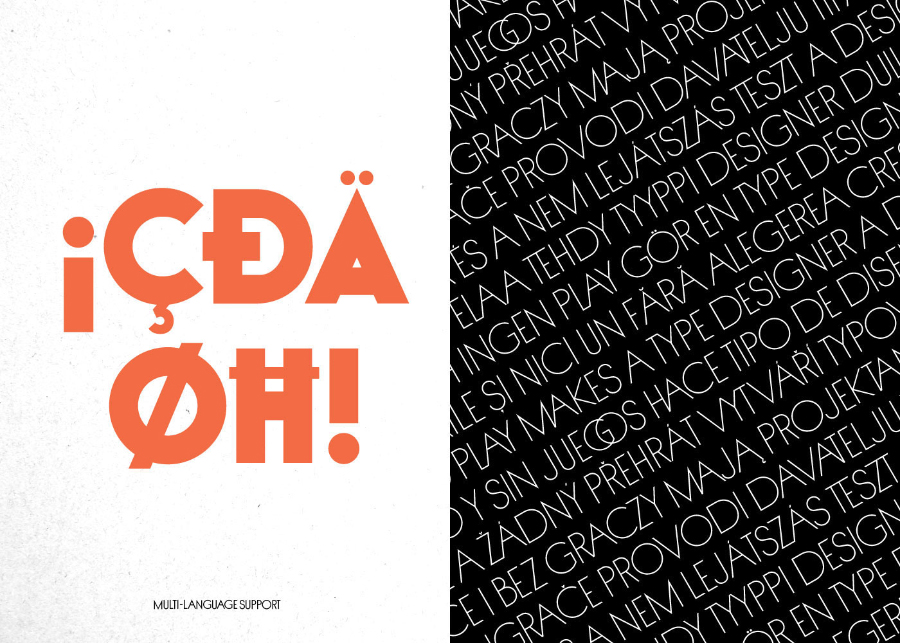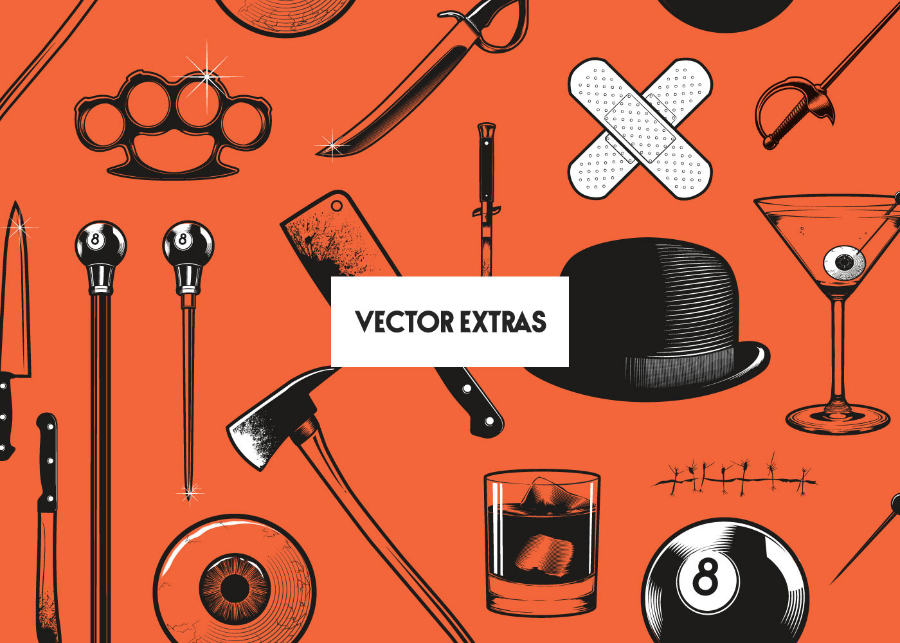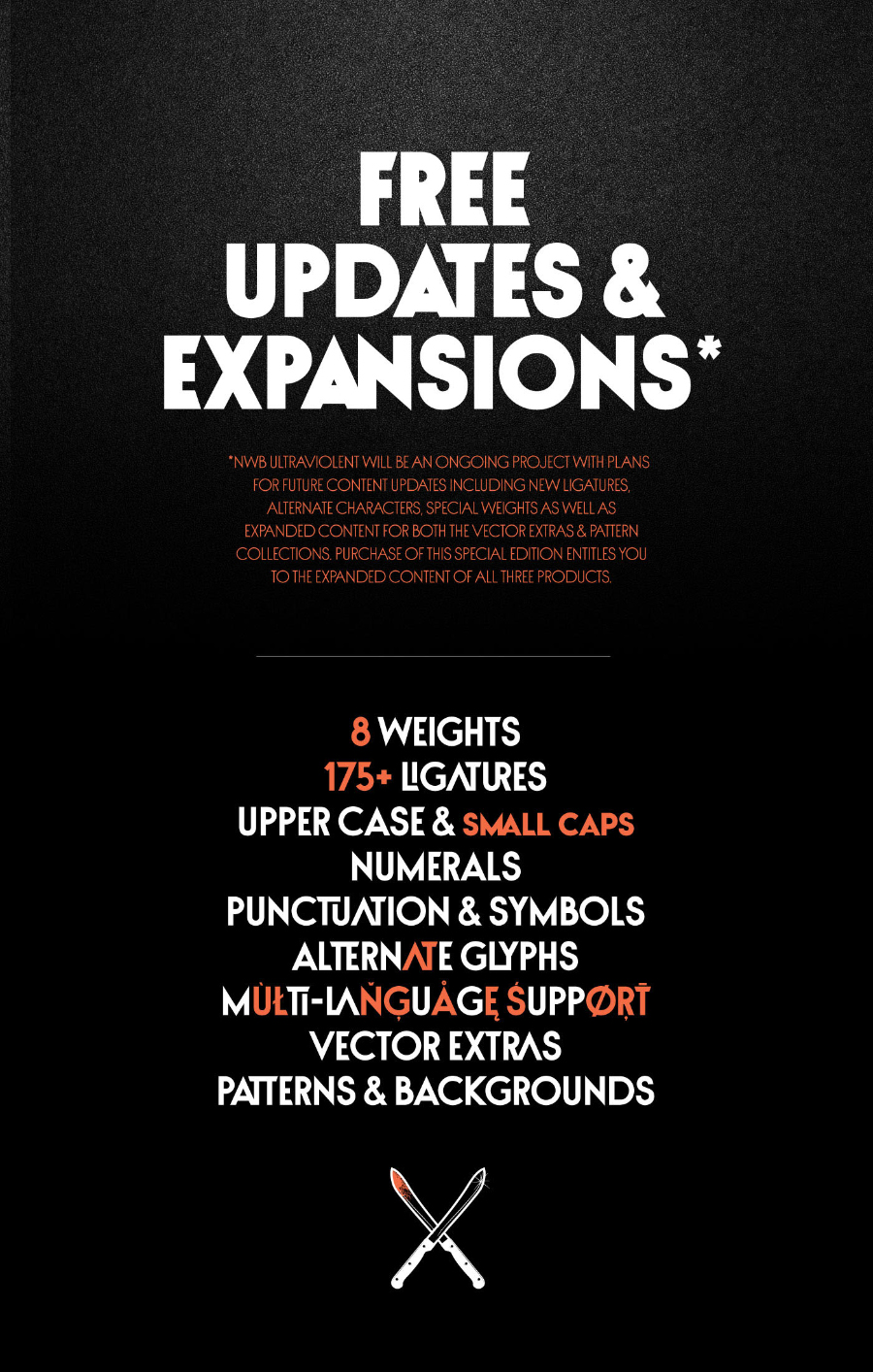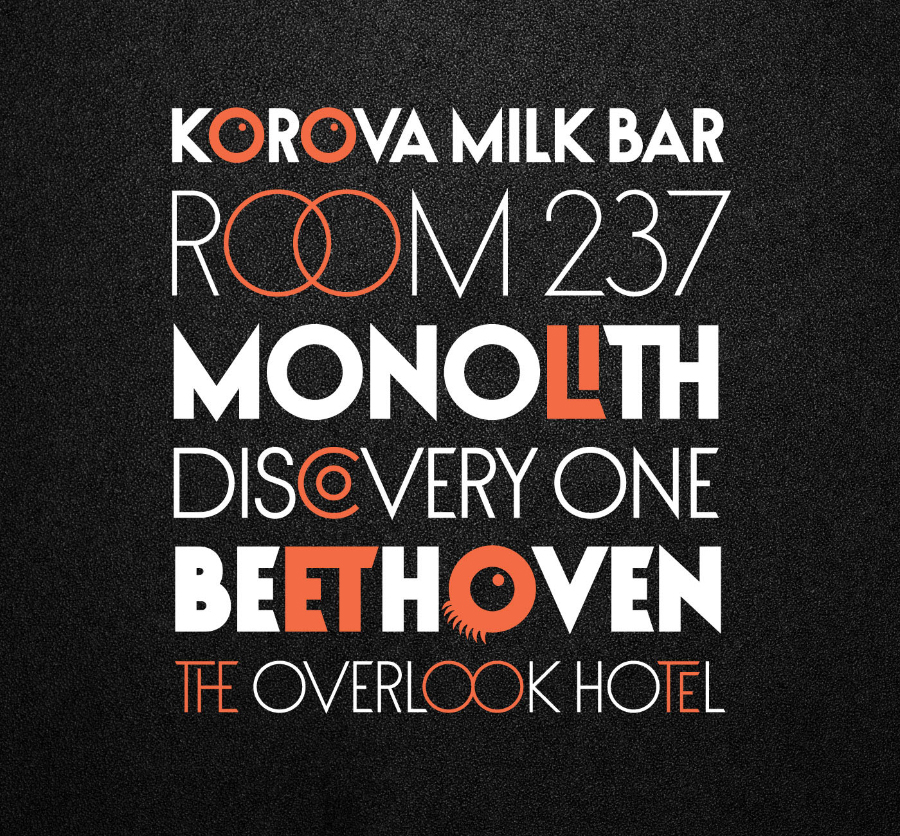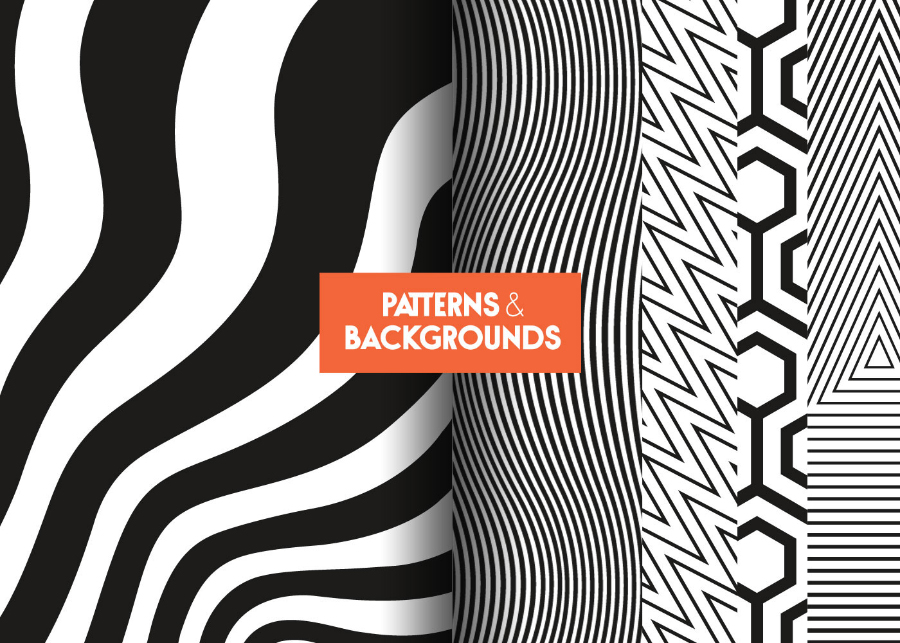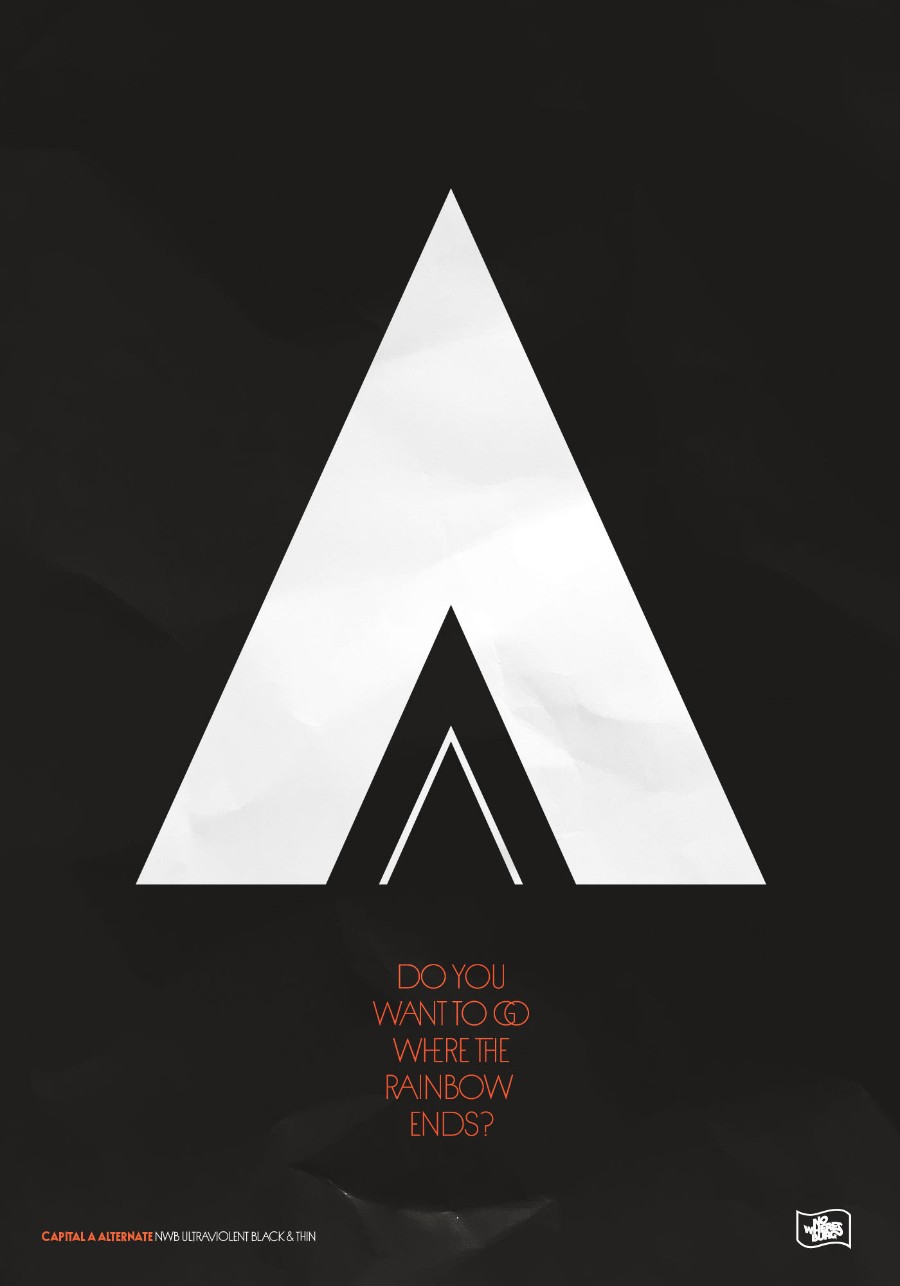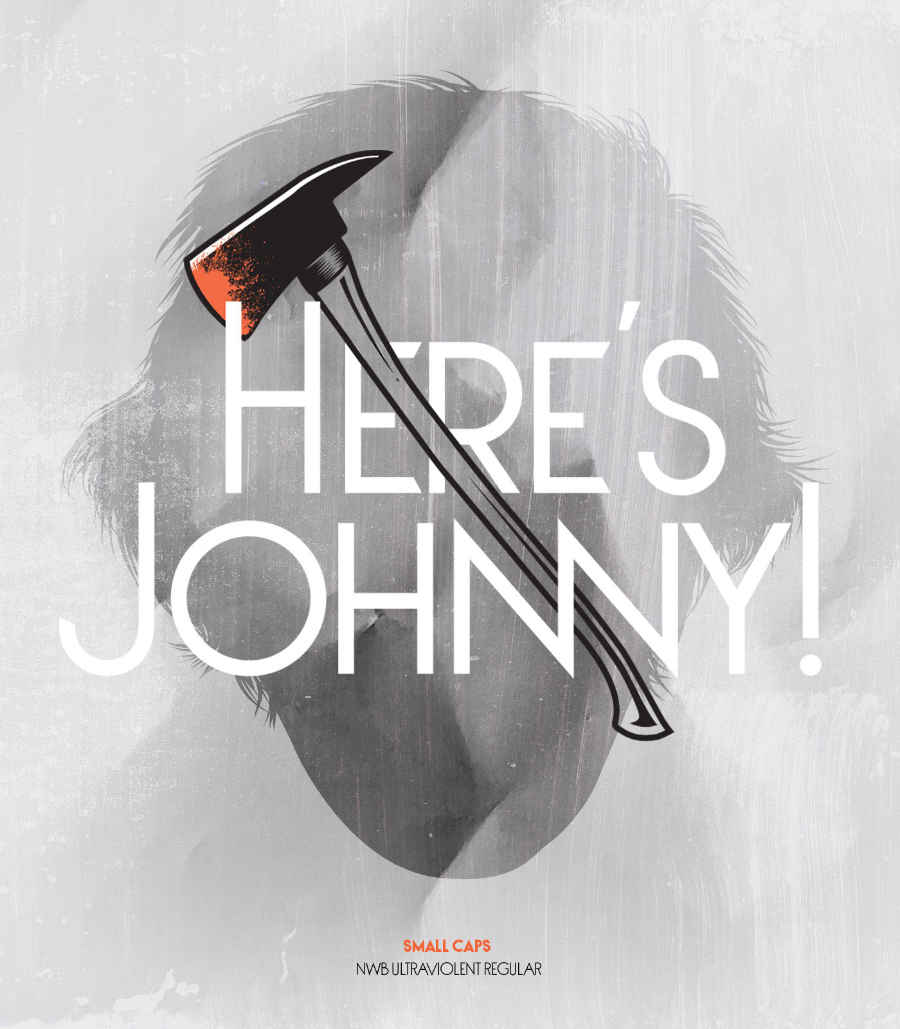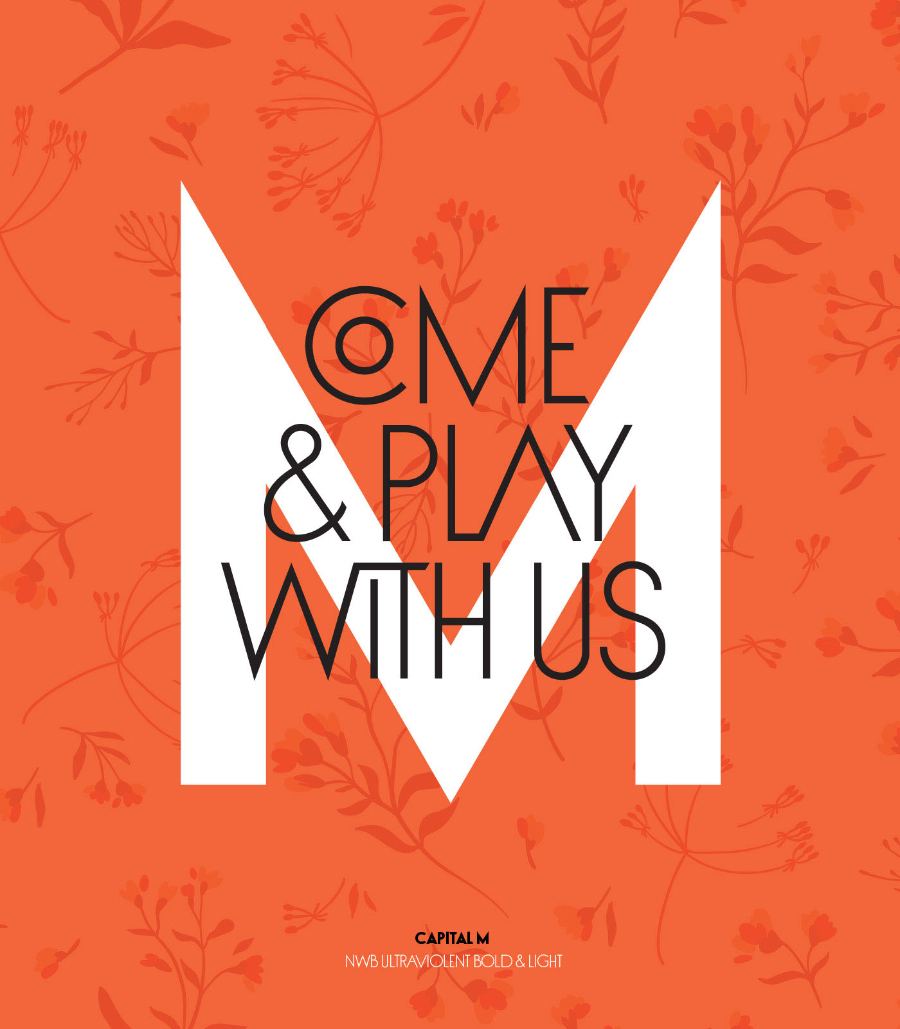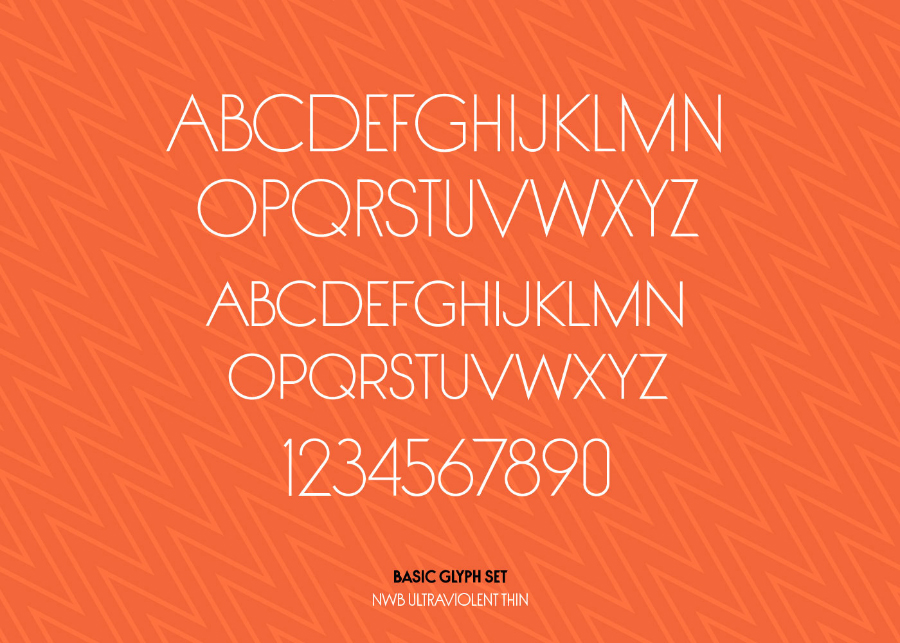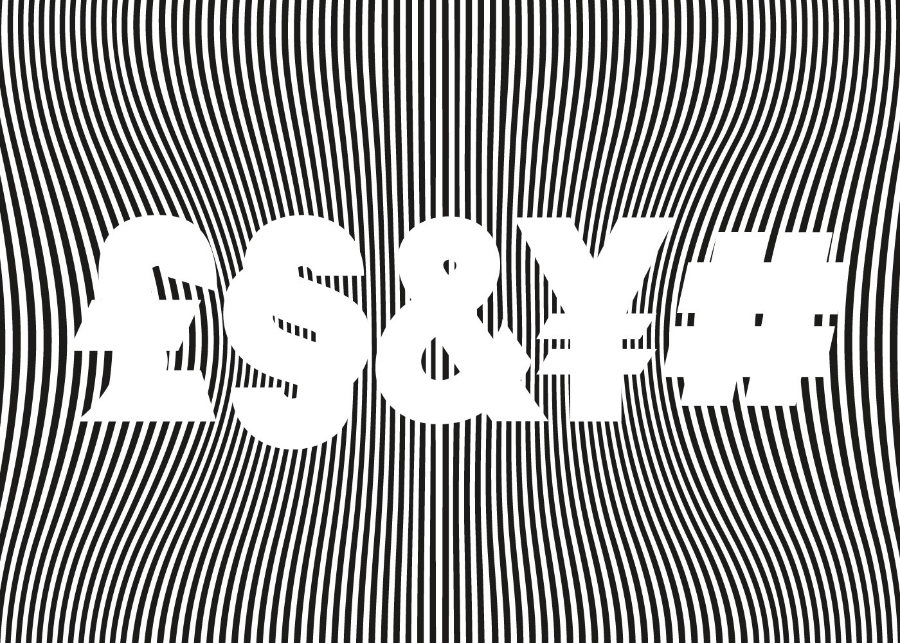
Ultraviolent常规免费字体
Ultraviolent Regular Free Font
Ultraviolent Regular Free字体是Nowheresburg的8重量几何无衬线字体字体之一。这是灵感来自发条橙的海报类型。此外,它的设计结合了Futura的美学与Avant Garde的复杂结扎结构以及Herb Lubalin的其他类型设计。因此,今天我们有一个干净,现代的旋转创造一个quirkly复古,但时尚的外观。